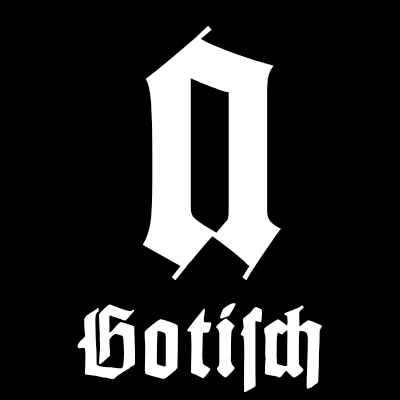
- 1934
- Gebrochene Schrift
Die Hermann-Gotisch wurde von Herbert Thannhaeuser für die Schriftgießerei Schelter & Giesecke, Leipzig entworfen und im Jahr 1934 veröffentlicht. Sie war eine zeitlang weiter im Angebot bei VEB Typoart, indem der Schelter & Giesecke nach der Gründung der DDR aufging.
Für die die private Nutzung gibt es eine kostenlose Version von Dieter Steffmann, die in UNZ-Kodierung bei Peter Wiegel zum Download bereit steht. Jedoch vertragen sich die feinen Innenlinien nicht besonders gut mit dem Prinzip der Auto-Tracing-Digitalisierung. Empfehlenswerter ist daher die Version von RMU Fonts, die unter dem Namen Staufer Gotisch erschienen ist.